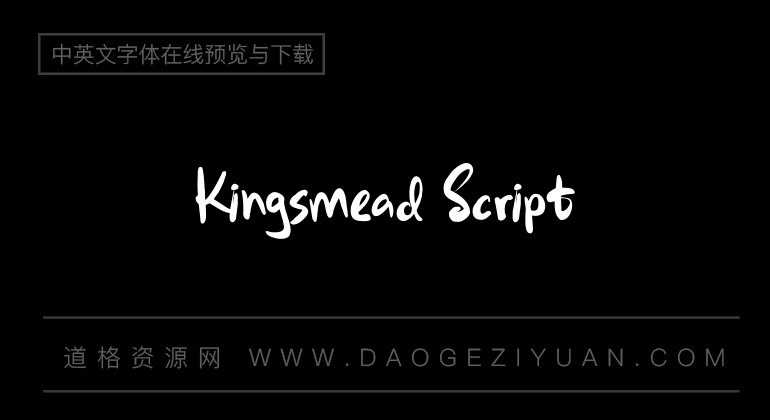
Kingsmead Script是一款古典风格的手写草书字体,它由Kingsmead字体公司开发。Kingsmead Script字体具有清晰的笔画,以及优雅而优美的设计。它具有英文、法文、德文、西班牙文和意大利文的支持,可以用于各种类型的文档,包括宣传册、海报、报纸、杂志和书籍等。Kingsmead Script字体具有可爱的外观,可以帮助您的文档更加精致。内容介绍
Kingsmead Script是一款非常不错的手写艺术字体,具有很好的视觉感,适合于文化类的宣传设计、商业类品牌的广告和产品包装设计以及个性化文字排版等较多场景。